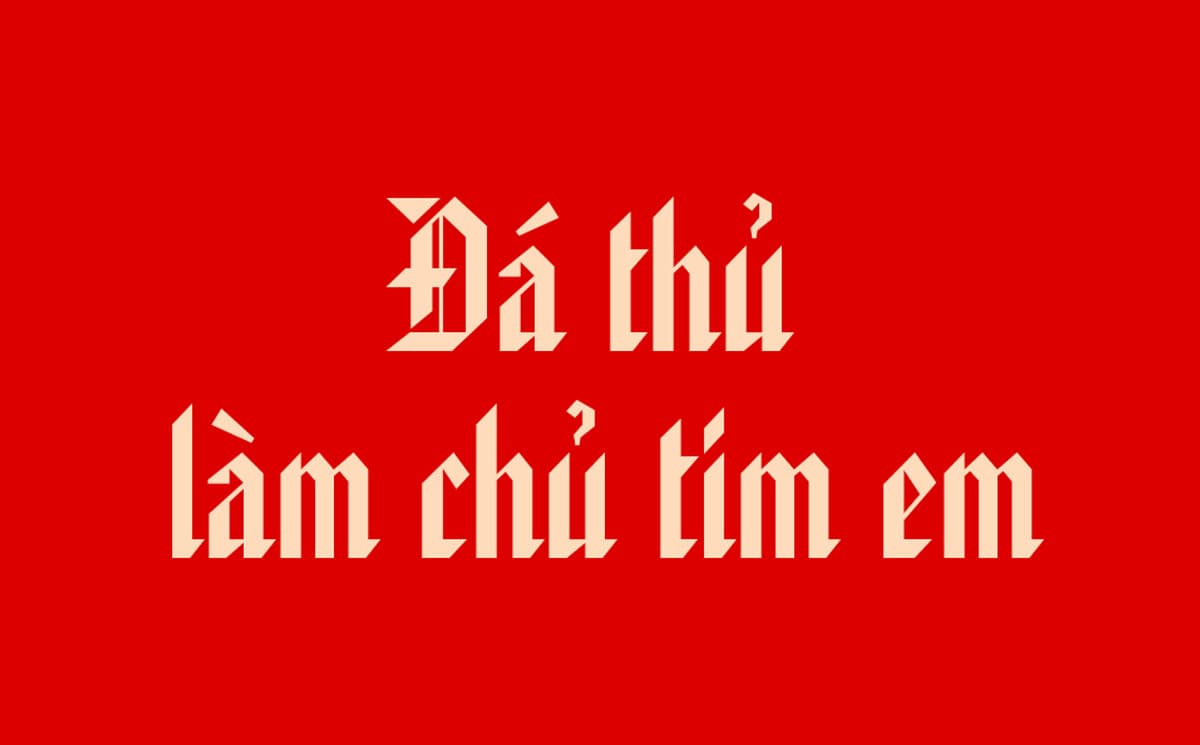
Giới Thiệu Font Chữ Cổ Điển UVN Hoa Kỳ Việt Hóa
UVN Hoa Kỳ Việt Hóa là một font chữ mang phong cách cổ điển, được thiết kế để mang đến sự trang nhã và thanh lịch cho các ấn phẩm. Với các đường nét tinh tế, uyển chuyển và chi tiết tỉ mỉ, font chữ này gợi lên vẻ đẹp cổ điển và sang trọng, phù hợp cho nhiều loại thiết kế. Phiên bản Việt hóa của UVN Hoa Kỳ tích hợp đầy đủ các ký tự tiếng Việt, đảm bảo tính liền mạch và thẩm mỹ khi sử dụng trong các ấn phẩm tiếng Việt. UVN Hoa Kỳ Việt Hóa đặc biệt phù hợp cho các dự án cần sự trang trọng và thanh lịch như thiệp mời, thiệp cưới, bìa sách, và poster sự kiện văn hóa. Các ký tự được thiết kế hài hòa, tạo nên một tổng thể đẹp mắt và ấn tượng, giúp truyền tải thông điệp một cách rõ ràng và hiệu quả. Sự kết hợp giữa vẻ đẹp cổ điển và sự hiện đại trong UVN Hoa Kỳ Việt Hóa mang lại sự mới mẻ và độc đáo cho các nhà thiết kế. Font chữ này không chỉ tăng cường tính thẩm mỹ cho các thiết kế mà còn giúp các ấn phẩm trở nên nổi bật và cuốn hút. Với UVN Hoa Kỳ Việt Hóa, mỗi thiết kế đều trở nên đặc biệt và mang đậm dấu ấn riêng.